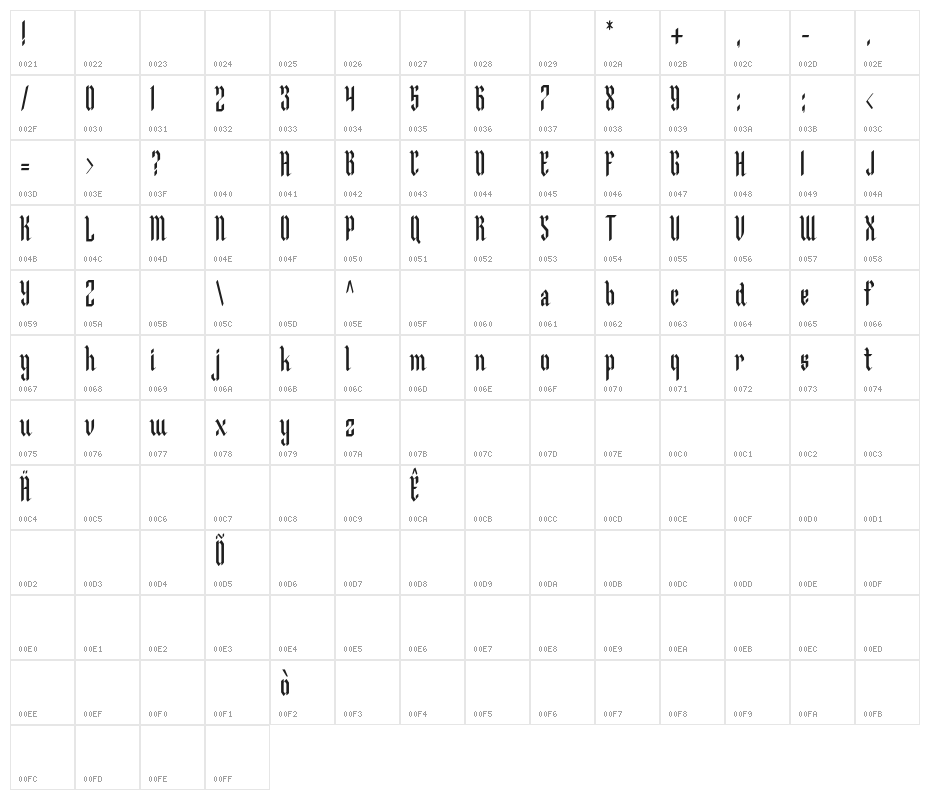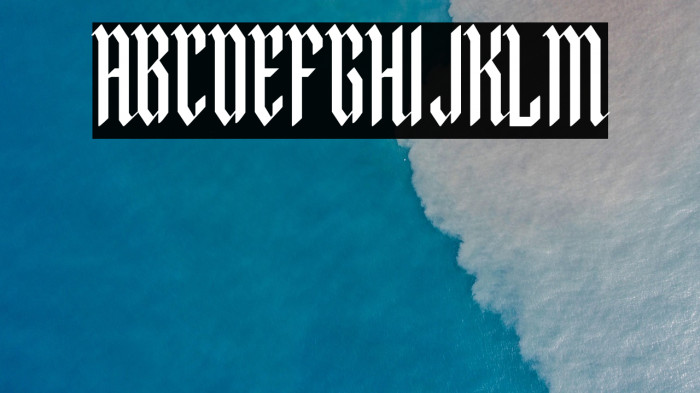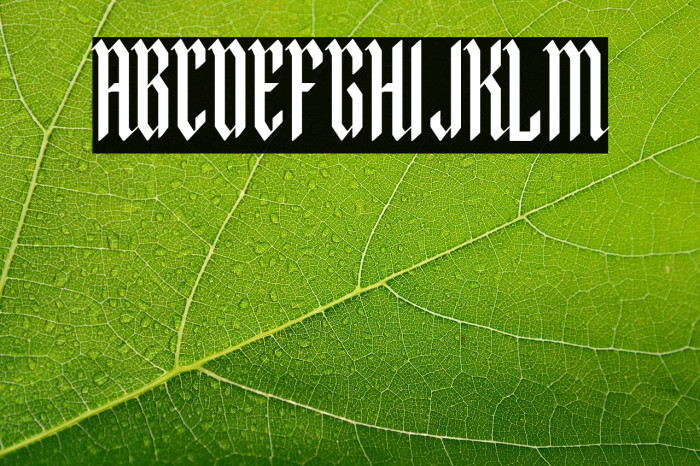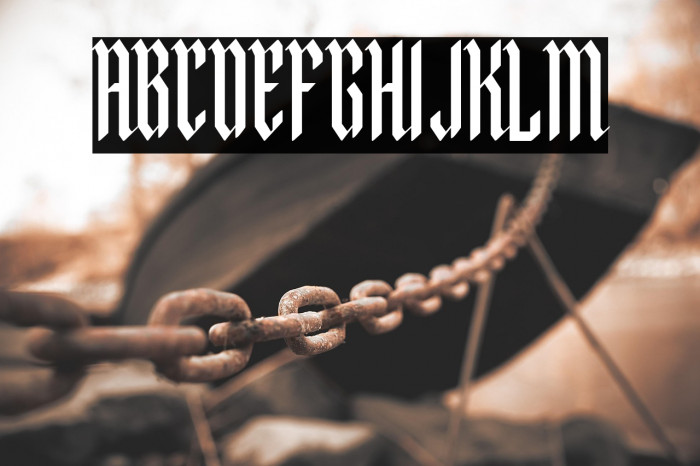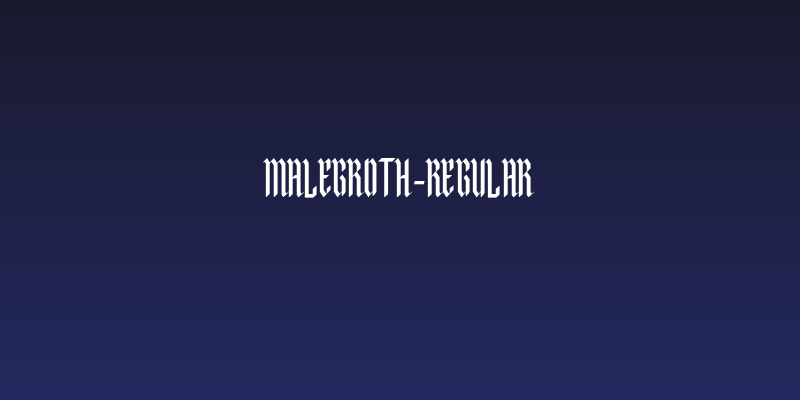
Malegroth-Regular Font
| Kategorien | Gothic |
| Gesamtstil | Vintage |
| Anwendungsfall | Logos, Headlines, Decorative text |
| Vorgeschlagene Projekte | Suitable for historical documents, gothic-themed designs, book covers, and branding that requires a classic and authoritative look. |